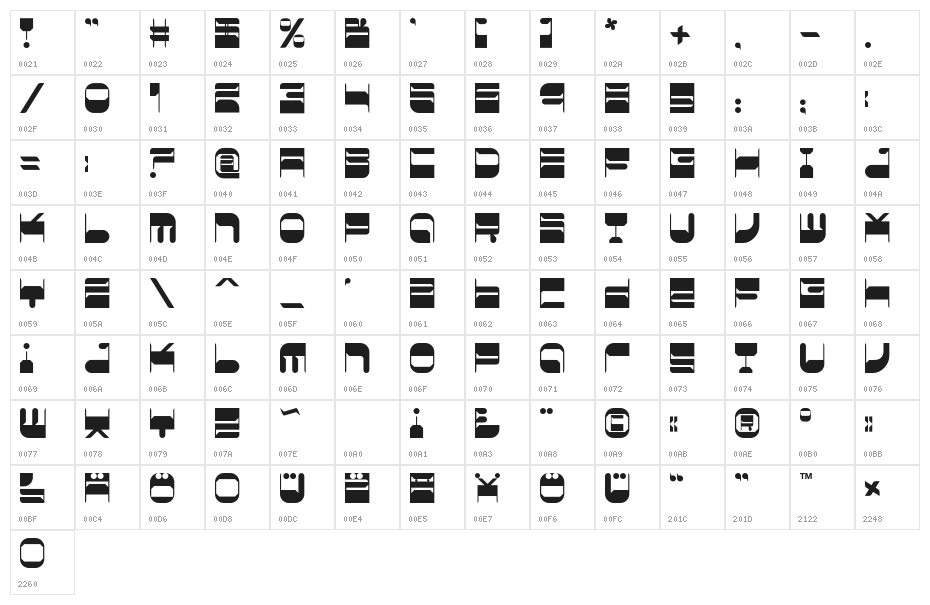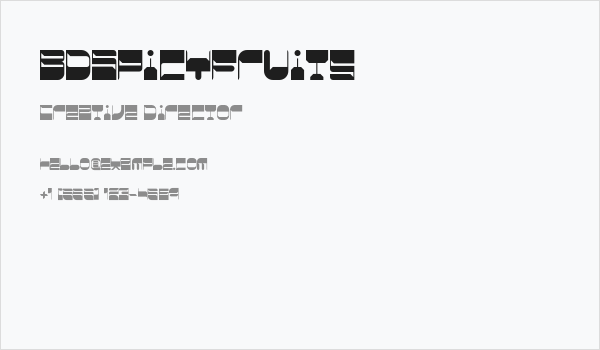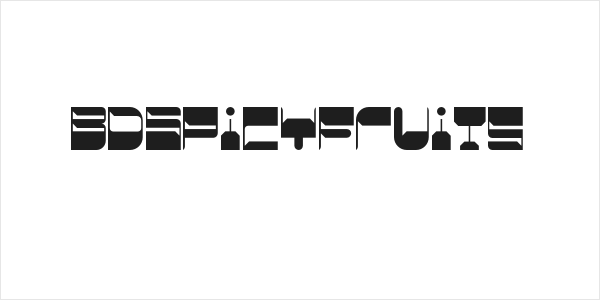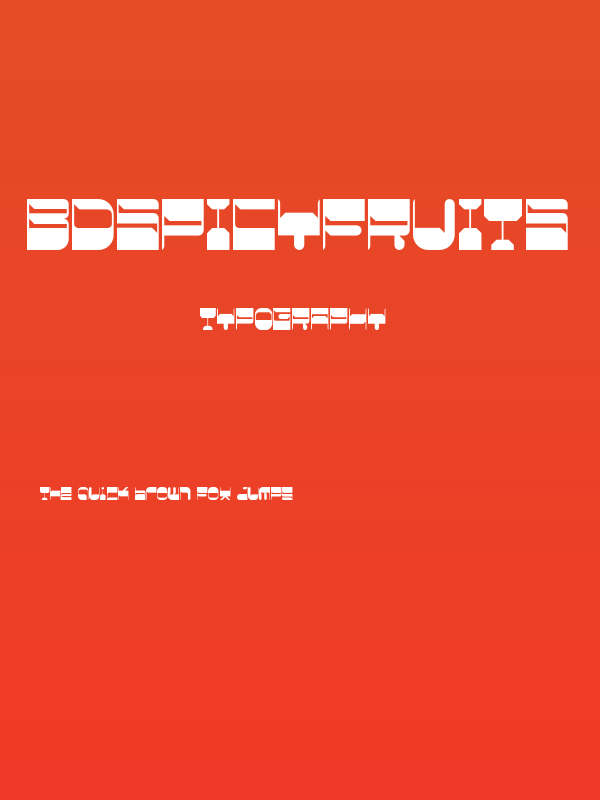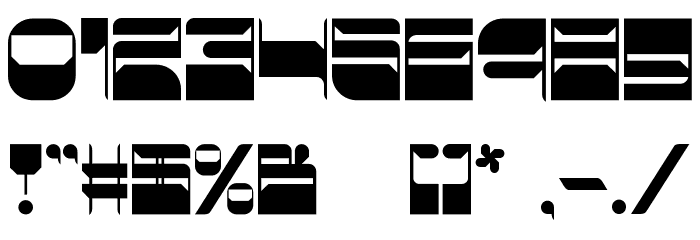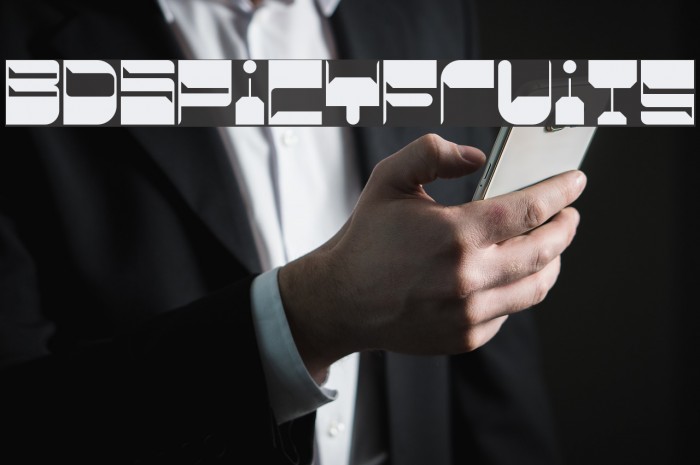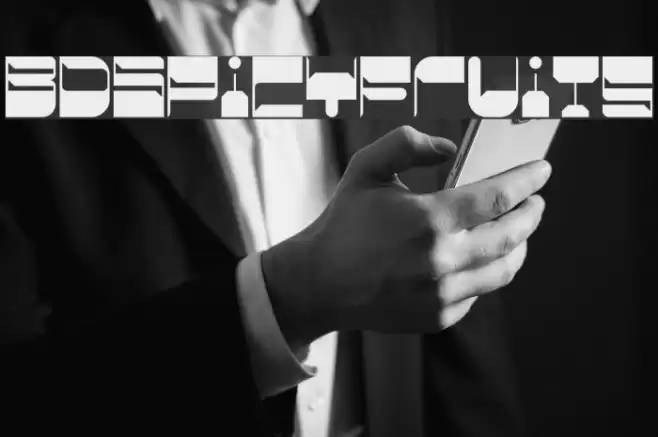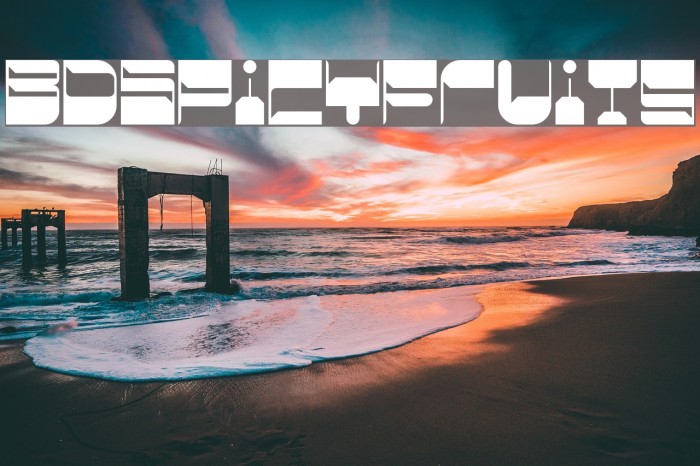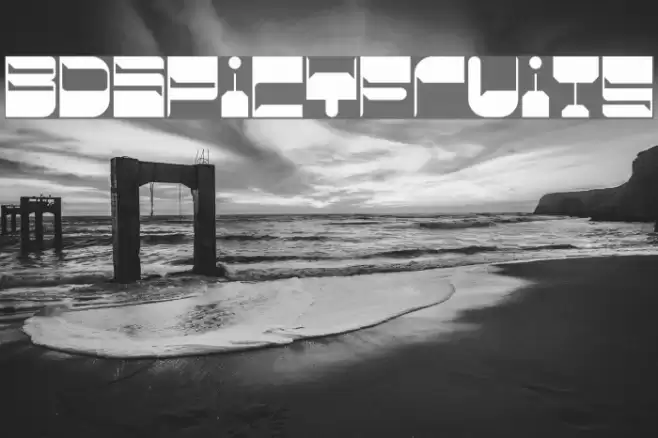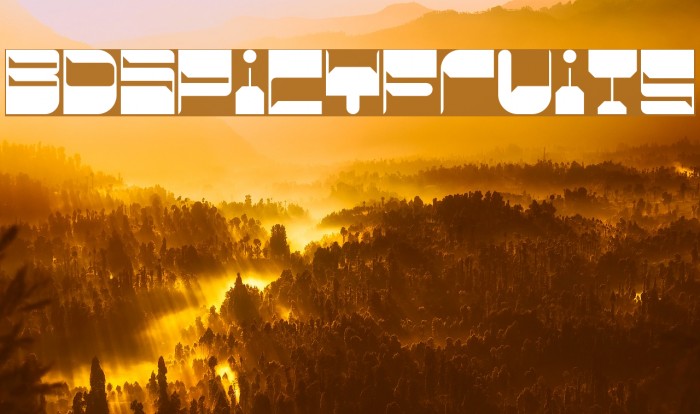
BDSpicyFruits Font
| Style général | Futuristic, Modern |
| Projets proposés | Ideal for technology branding, sci-fi themed posters, video game titles, and modern advertising campaigns. |